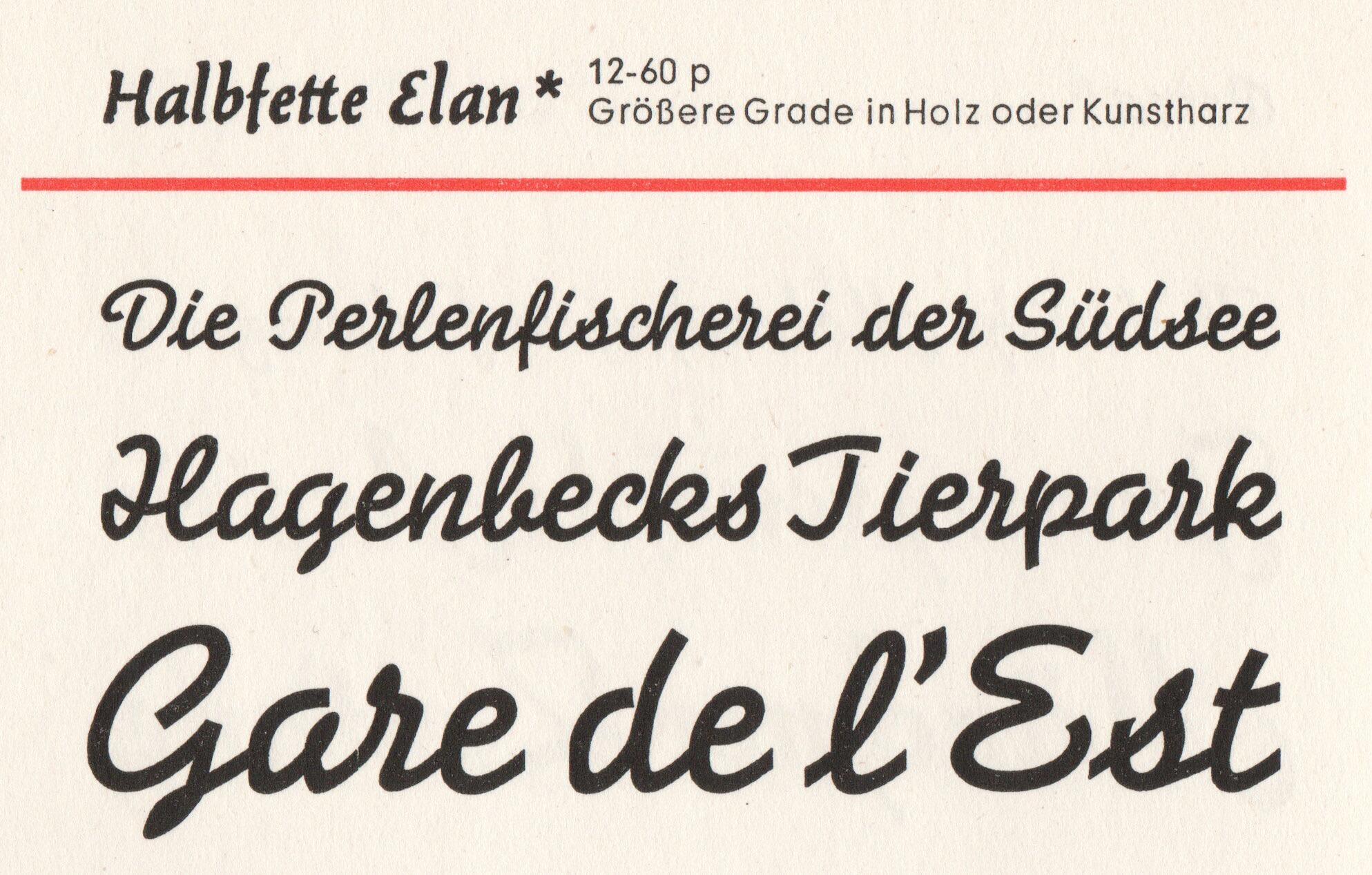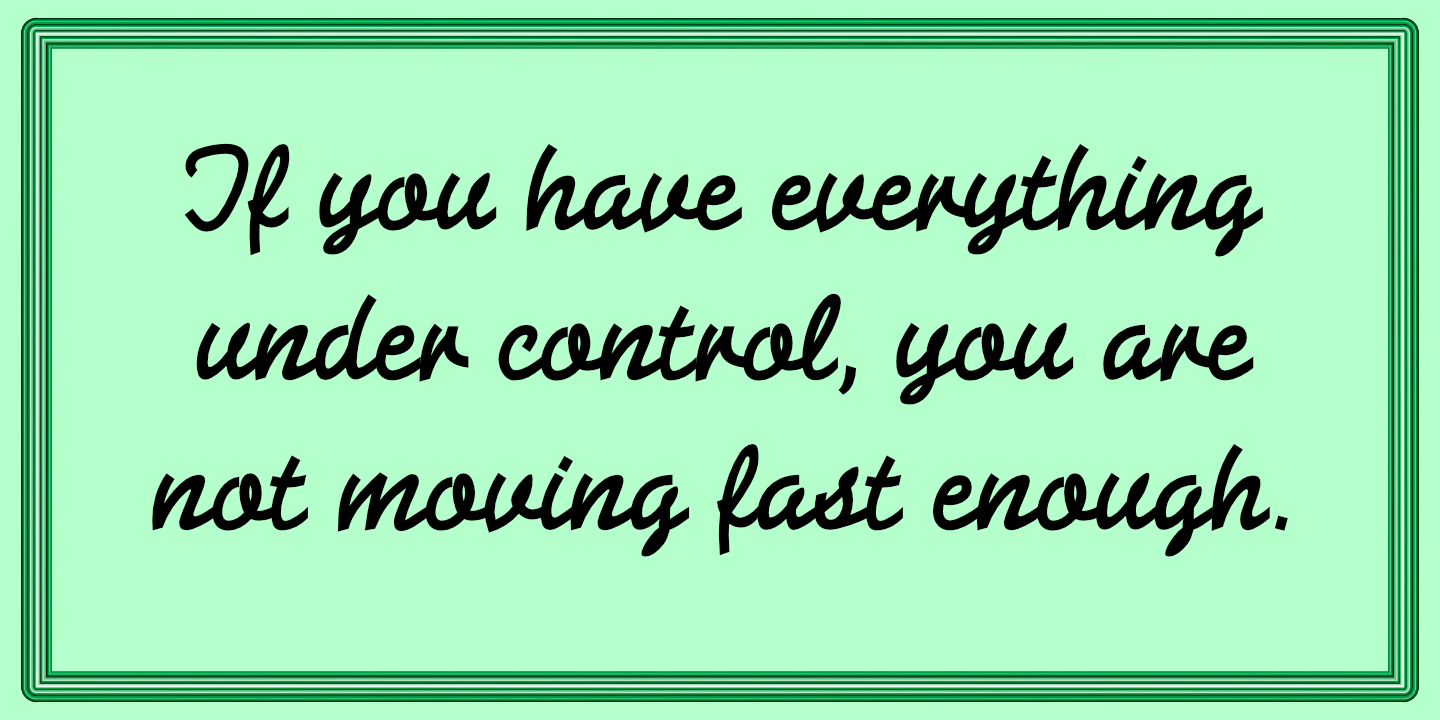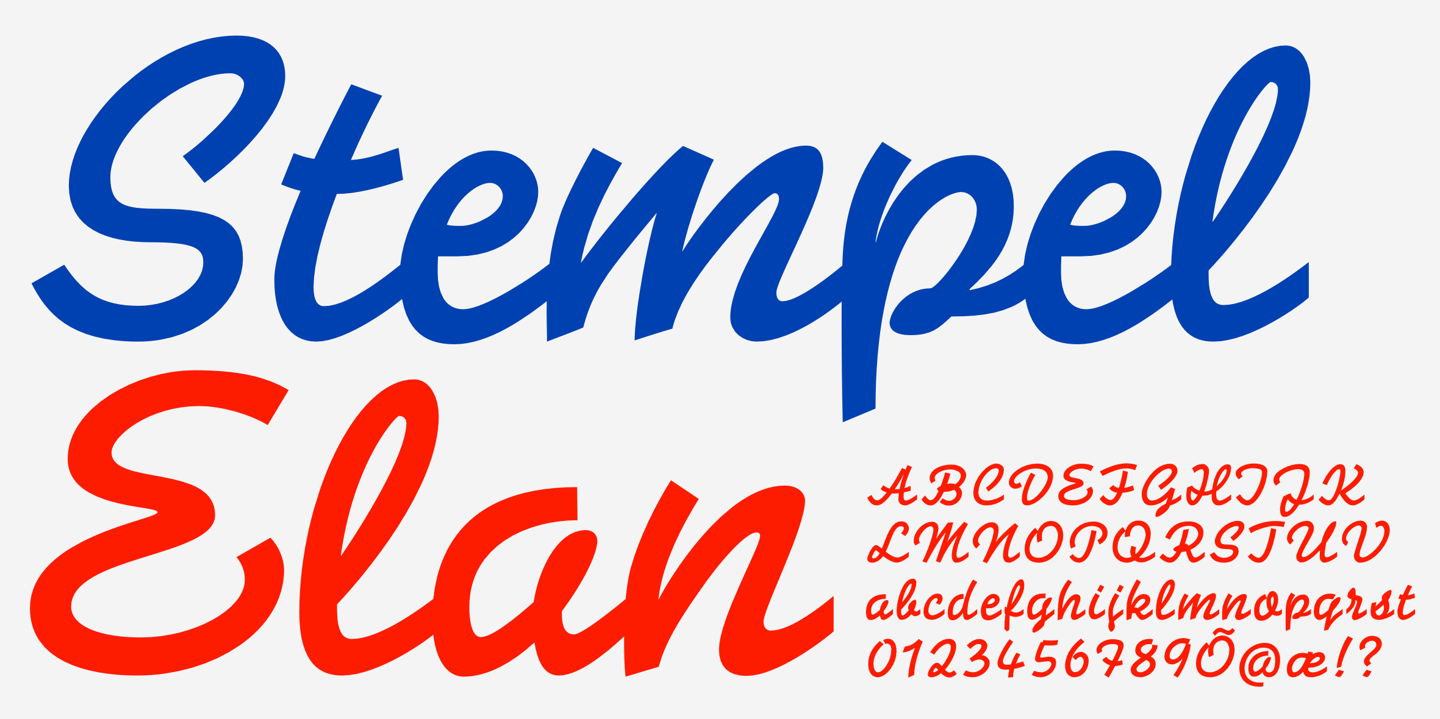
• 1936
• Antiqua Schreibschrift
Die Elan ist eine verbundene, informelle Schreibschrift von Hans Möhring und erschien 1937 bei der D. Stempel AG im Fahrwasser erfolgreicher Werbeschreibschriften wie der Signal der H. Berthold AG. Die Grundschrift ist halbfett. Eine zarte Version wurde später nachgelegt.
Digitalisierungen gibt es als Stempel Elan (von Frank Grießhammer) und Gmuender Elan Pro (von RMU Fonts).
Original-Bleisatz-Muster der Stempel AG
Digitalisierung als Stempel Elan
Digitalisierung als Gmuender Elan Pro